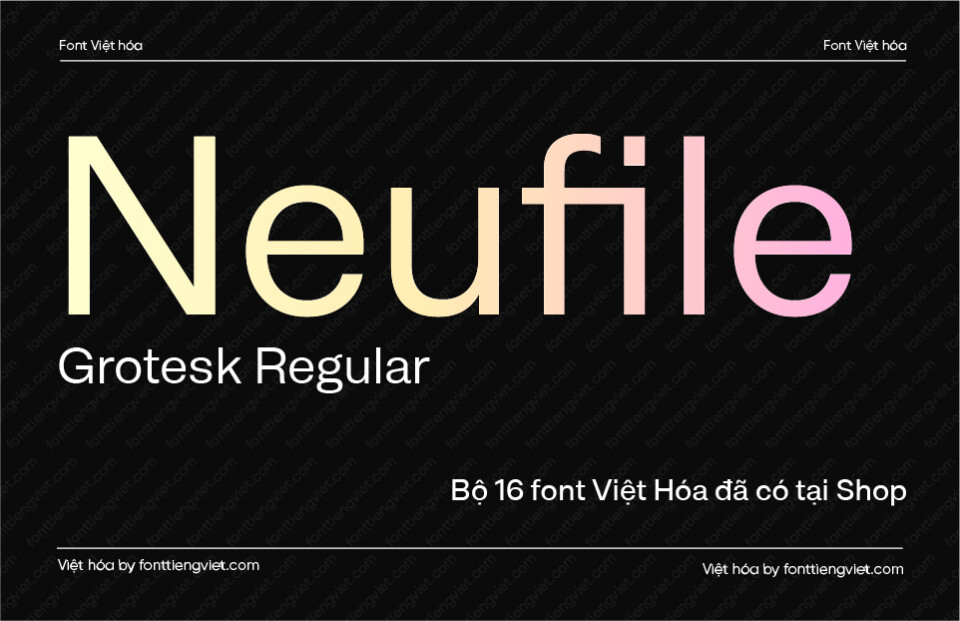
Tải Ngay Font Việt hóa 1FTV VIP Neufile Grotesk Regular Miễn Phí Cho Thiết Kế Chuyên NghiệpGiới thiệu về Font Việt hóa 1FTV VIP Neufile Grotesk RegularTrong thế giới đồ họa hiện đại, việc lựa chọn một bộ Font Miễn Phí chất lượng luôn là ưu tiên hàng đầu của các nhà thiết kế. Font Việt hóa 1FTV VIP Neufile Grotesk Regular là một phiên bản đặc biệt được tinh chỉnh kỹ lưỡng để phù hợp với ngôn ngữ tiếng Việt. Đây là kiểu chữ thuộc họ Grotesk, mang phong cách tối giản nhưng vô cùng mạnh mẽ và tinh tế. Neufile Grotesk được biết đến với cấu trúc hình học chuẩn xác, các nét chữ rõ ràng và không lỗi thời, giúp truyền tải thông điệp một cách trực diện nhất. Khi được đội ngũ 1FTV thực hiện Việt hóa, bộ font này đã khắc phục hoàn toàn các lỗi về dấu câu, mang lại sự đồng nhất tuyệt đối cho văn bản tiếng Việt. Đối với những người đang tìm kiếm một giải pháp typography vừa hiện đại vừa dễ đọc, phiên bản Regular này chính là sự lựa chọn không thể bỏ qua.Đặc điểm nổi bật của Font Việt hóa 1FTV VIP Neufile Grotesk RegularThiết kế hiện đại và linh hoạtĐặc trưng lớn nhất của Font Việt hóa 1FTV VIP Neufile Grotesk Regular chính là sự cân bằng giữa nét cổ điển của sans-serif và tư duy thiết kế đương đại. Các ký tự được thiết kế với độ tương phản thấp, tạo cảm giác mượt mà và dễ chịu cho mắt người đọc ngay cả khi sử dụng trong thời gian dài. Khoảng cách giữa các chữ cái (kerning) được tối ưu hóa để đảm bảo văn bản luôn đều đặn và chuyên nghiệp. Điều này cực kỳ quan trọng đối với các bạn học sinh và sinh viên khi trình bày các bài thuyết trình hoặc báo cáo khoa học cần sự chỉn chu.Khả năng ứng dụng đa dạng trong thực tếNhờ vào vẻ ngoài sạch sẽ, Font Việt hóa 1FTV VIP Neufile Grotesk Regular cực kỳ đa năng. Bạn có thể sử dụng nó cho các tiêu đề chính trong website, nội dung đoạn văn trên blog hoặc thậm chí là thiết kế bộ nhận diện thương hiệu. Trong môi trường học đường, bộ font này giúp các tài liệu giảng dạy trở nên hiện đại và bắt mắt hơn, kích thích tinh thần học tập của học sinh. Sự rõ ràng của nét chữ Regular giúp văn bản in ấn trên giấy hay hiển thị trên màn hình điện tử đều đạt độ sắc nét cao nhất.Lợi ích khi sử dụng Font Việt hóa 1FTV VIP Neufile Grotesk RegularSử dụng bộ font này không chỉ giúp tác phẩm của bạn đẹp hơn mà còn thể hiện sự tôn trọng đối với người xem thông qua việc sử dụng tiếng Việt có dấu chuẩn xác. Việc tải và cài đặt Font Việt hóa 1FTV VIP Neufile Grotesk Regular vô cùng đơn giản, tương thích tốt với các phần mềm thiết kế phổ biến như Adobe Photoshop, Illustrator hay các ứng dụng văn phòng như Microsoft Word và PowerPoint. Đây là công cụ đắc lực để biến những ý tưởng sơ khai thành những sản phẩm đồ họa chuyên nghiệp và có chiều sâu thẩm mỹ.Kết luận và hướng dẫn tải fontHy vọng rằng bộ font này sẽ mang lại nguồn cảm hứng mới cho các dự án sáng tạo của bạn. Sự kết hợp giữa tư duy thiết kế quốc tế và bản sắc Việt hóa chuyên sâu đã tạo nên một sản phẩm typography hoàn hảo cho mọi nhu cầu. Hãy nhanh tay truy cập trang Font Miễn Phí, Font Việt Hóa, Font Việt hóa 1FTV VIP Neufile Grotesk Regular để sở hữu ngay bộ chữ tuyệt đẹp này hoàn toàn miễn phí. Đừng quên chia sẻ tài nguyên hữu ích này đến bạn bè và đồng nghiệp để cùng nhau xây dựng cộng đồng thiết kế Việt Nam ngày càng phát triển mạnh mẽ và chất lượng hơn.
Font Việt hóa 1FTV VIP Neufile Grotesk Regular